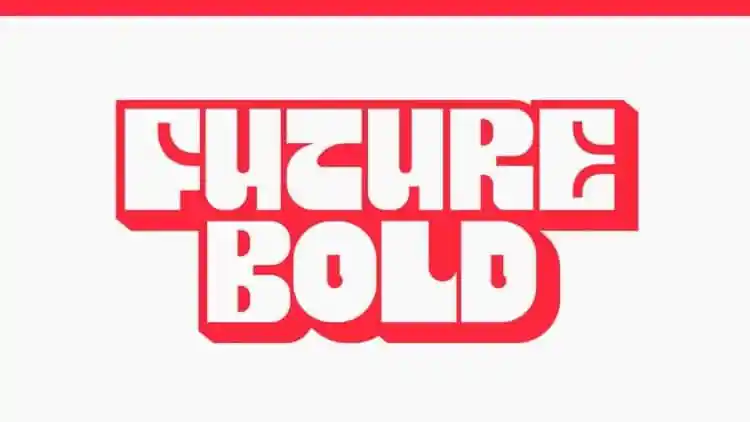
A fonte Future Bold Display é uma escolha perfeita para quem busca uma impressão forte e original, destacando-se no campo do design visual. Ela foi criada por Dishant Mehlawwat, representando um peso de exibição extremamente densoado que traz consigo muitas características únicas. Ideal para grandes títulos, anúncios, rótulos e embalagens, além de qualquer aplicação que precise de uma tipografia com impacto visual imediato. Essa fonte se destaca como um recurso valioso em projetos gráficos modernos e criativos, permitindo que o design seja levado ao extremo da sofisticação e impacto. Seja para uso em materiais publicitários ou arquitetônicos, a Future Bold Display não deixará ninguém indiferente.